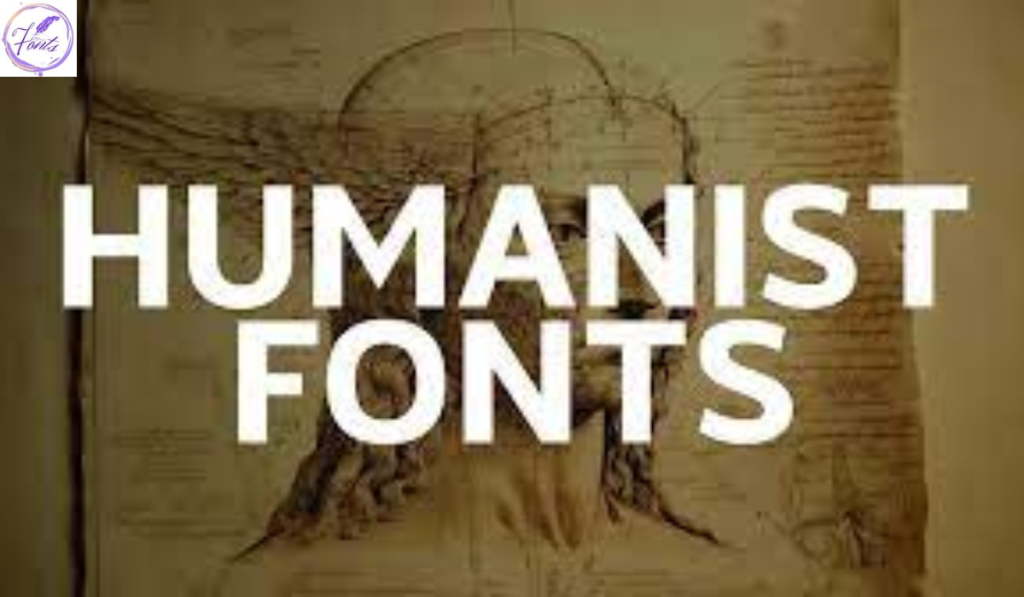
Humanist font việt hóa
Tác giả: Aldus Manutius, Nicolas Jenson, Francesco Griffo
Phân loại: Cá tính, Độc đáo, Nhân văn, Cổ điển
Kiểu chữ: Có chân, Không chân
Độ dày: Regular, Italic, Bold, Bold Italic
Humanist font là một loại phông chữ sans-serif, được thiết kế để mang lại cảm giác tự nhiên và dễ đọc. Được phát triển bởi các nhà thiết kế hàng đầu như Aldus Manutius, Nicolas Jenson, Francesco Griffo vào giai đoạn 1460-1470, loại phông chữ này nổi bật với các đường nét mềm mại và tỉ mỉ, tạo cảm giác thân thiện và gần gũi. Phiên bản việt hóa của Humanist font hỗ trợ đầy đủ các ký tự tiếng Việt, giúp người dùng dễ dàng áp dụng trong nhiều dự án thiết kế từ in ấn đến kỹ thuật số.
Đánh giá humanist font
Humanist font nhận được nhiều đánh giá tích cực từ cộng đồng thiết kế nhờ vào tính thẩm mỹ và khả năng ứng dụng đa dạng. Các nhà thiết kế đánh giá cao sự linh hoạt của font này khi sử dụng cho các dự án yêu cầu sự rõ ràng và dễ đọc. Humanist font đặc biệt phù hợp cho các văn bản dài, bài viết trên web và các tài liệu in ấn, nhờ vào khả năng duy trì sự dễ nhìn và thoải mái cho mắt người đọc. Font này cũng rất được ưa chuộng trong việc thiết kế logo và thương hiệu.